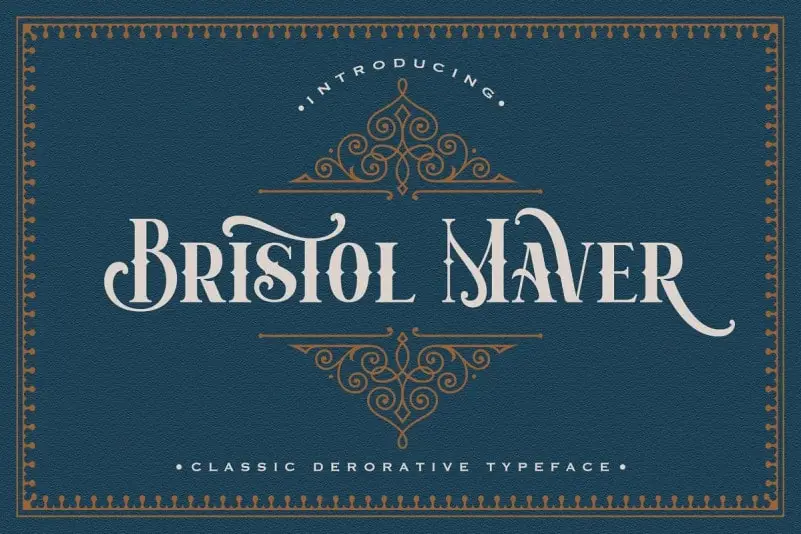
Bristol Maver Display Font – Download Grátis
A Bristol Maver Display Font é uma criação moderna inspirada no movimento arquitetônico e decorativo, oferecendo visuais excepcionais que destacam-se em qualquer contexto visual. Com um contrastre alto entre caracteres, ligações acentuadas e várias variante de caracteres distintas, ela se destaca como uma fonte de display perfeita para uso em aplicativos digitais modernos ou em materiais impressos de alta qualidade. Esta fonte é especialmente útil para design gráfico, editorial e branding digital, onde deseja destacar visivelmente o seu trabalho com um estilo único e atraente. Com sua versatilidade e qualidade impressionante, a Bristol Maver Display Font se transforma em uma escolha inteligente para qualquer designer profissional que busca adicionar personalidade à sua identidade visual ou conteúdo digital.